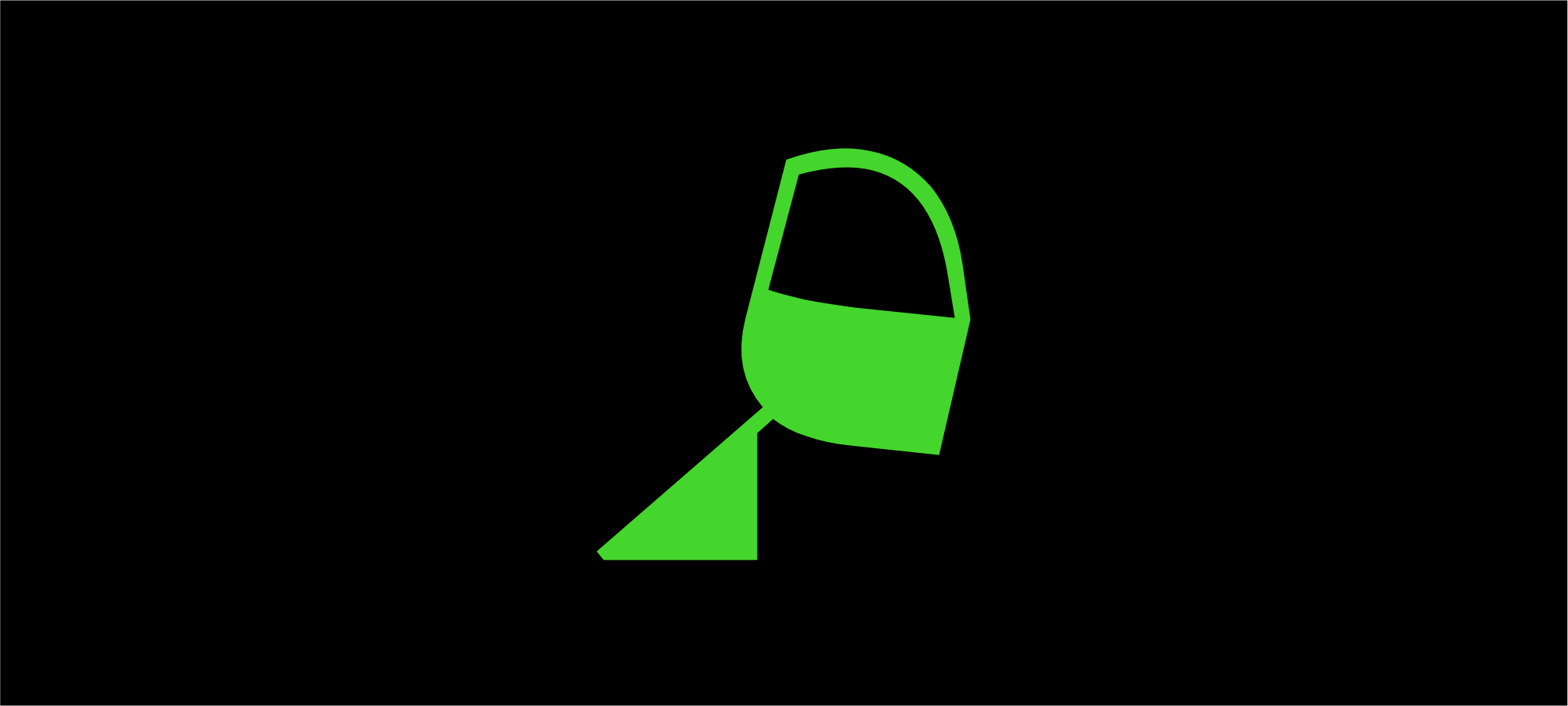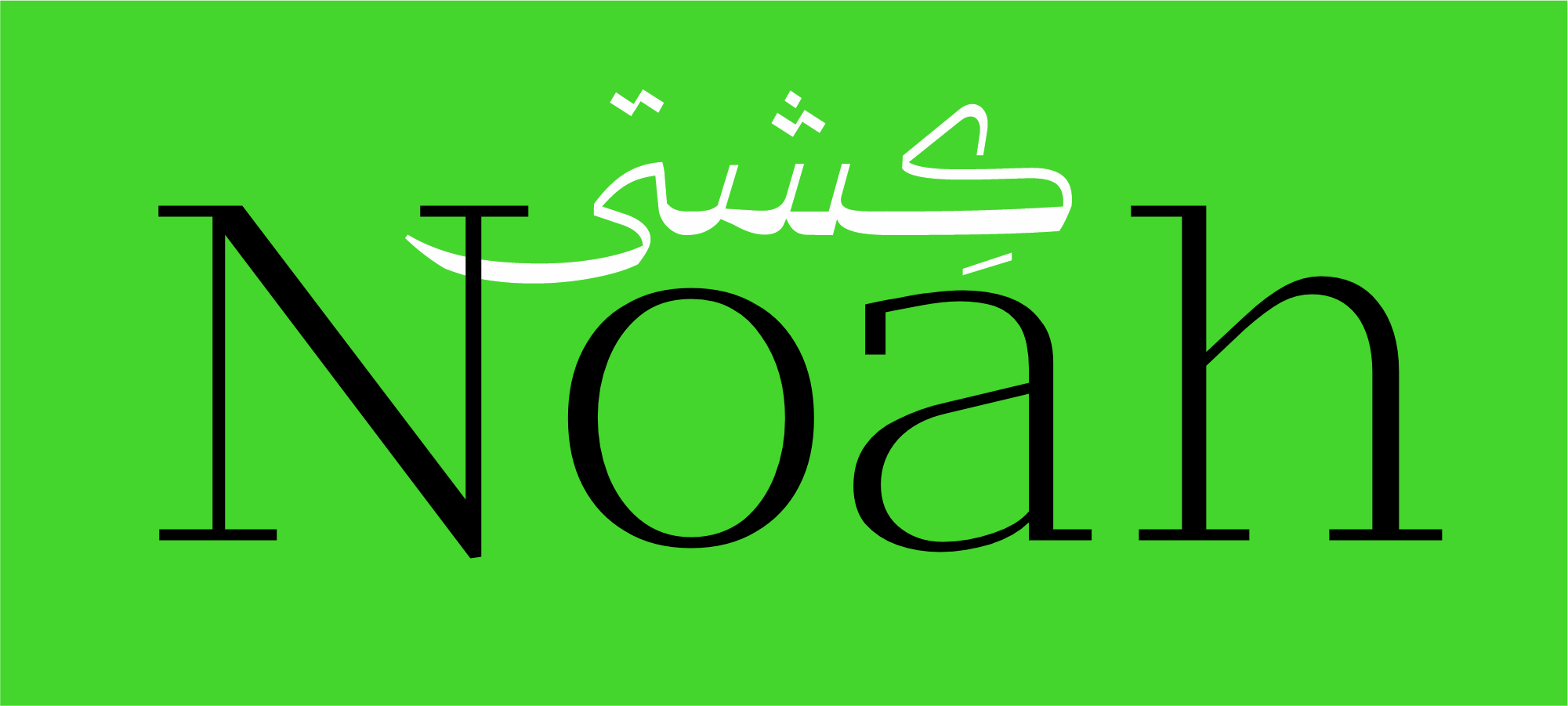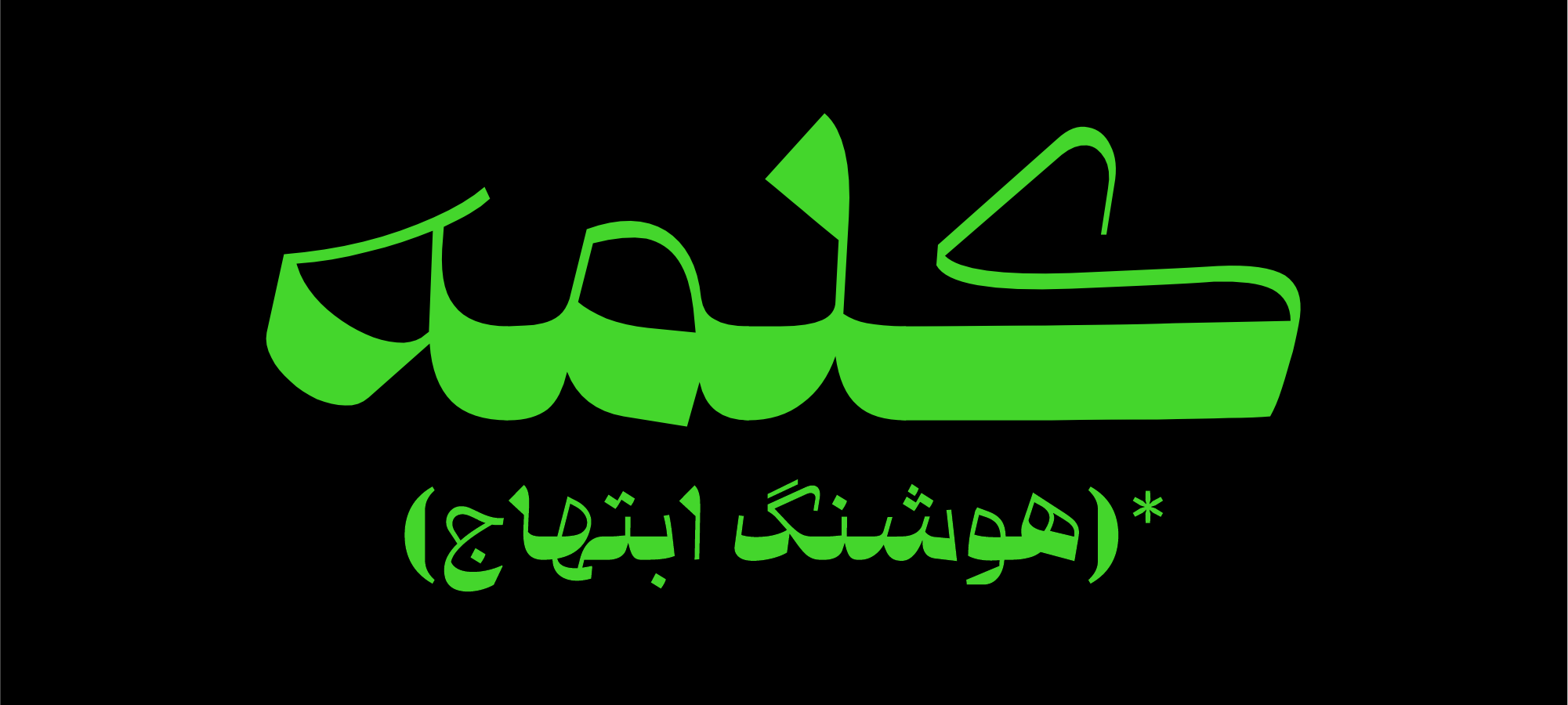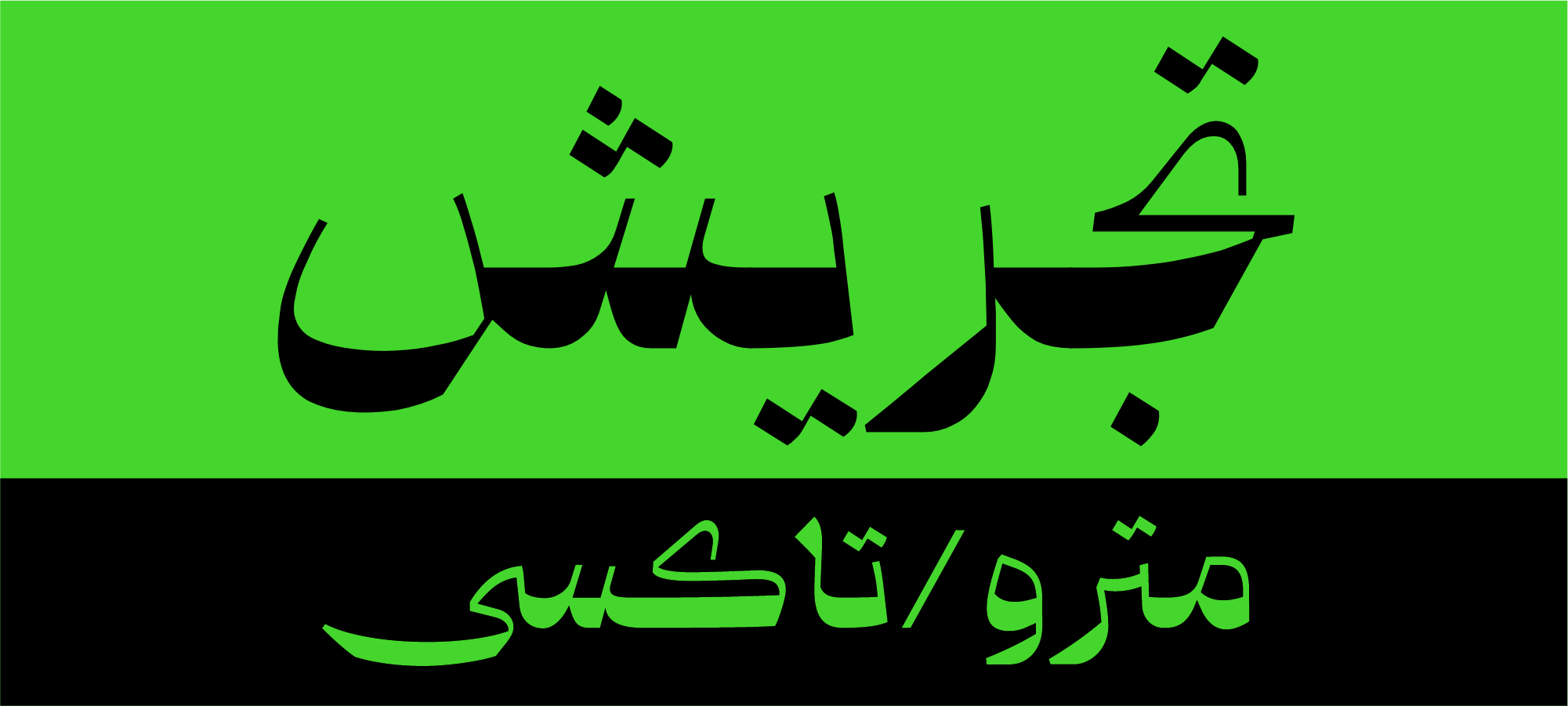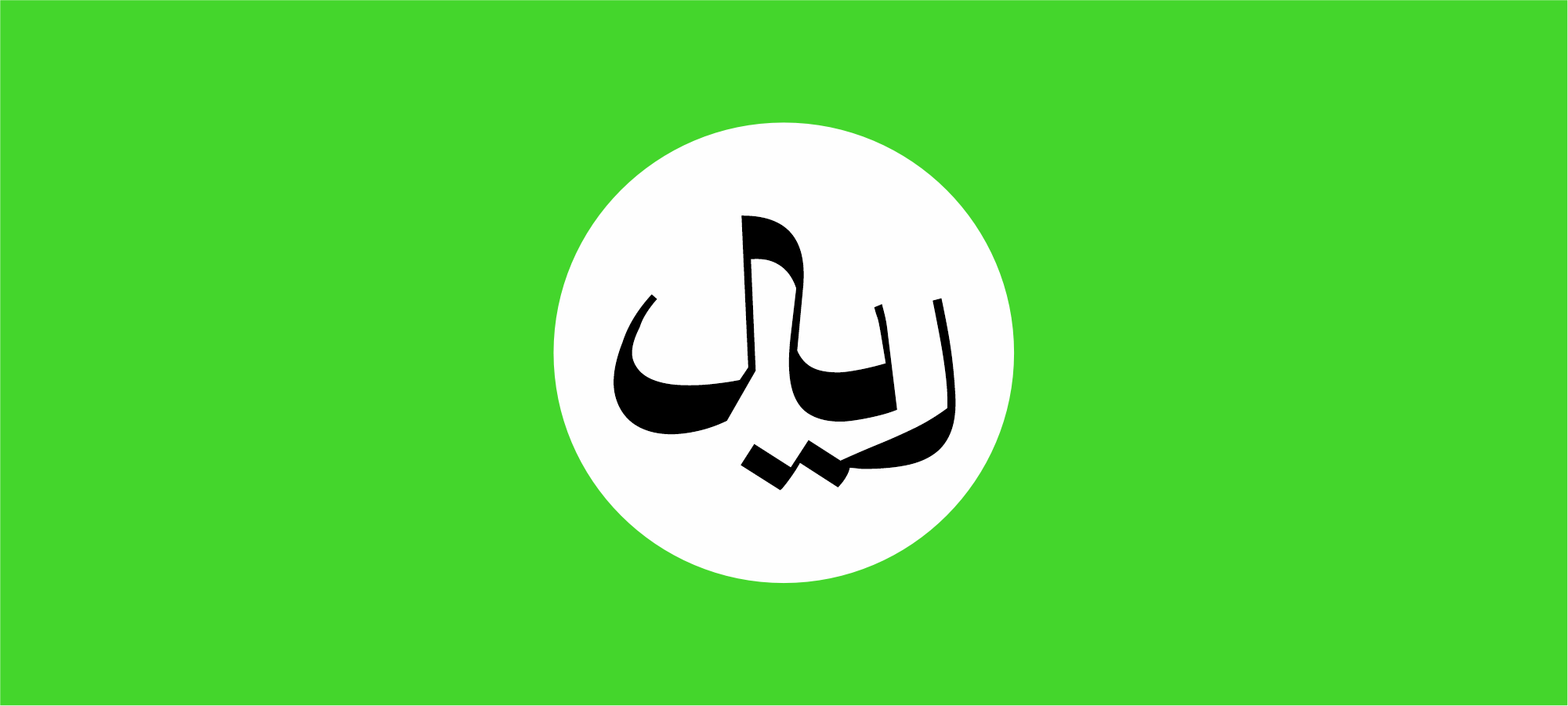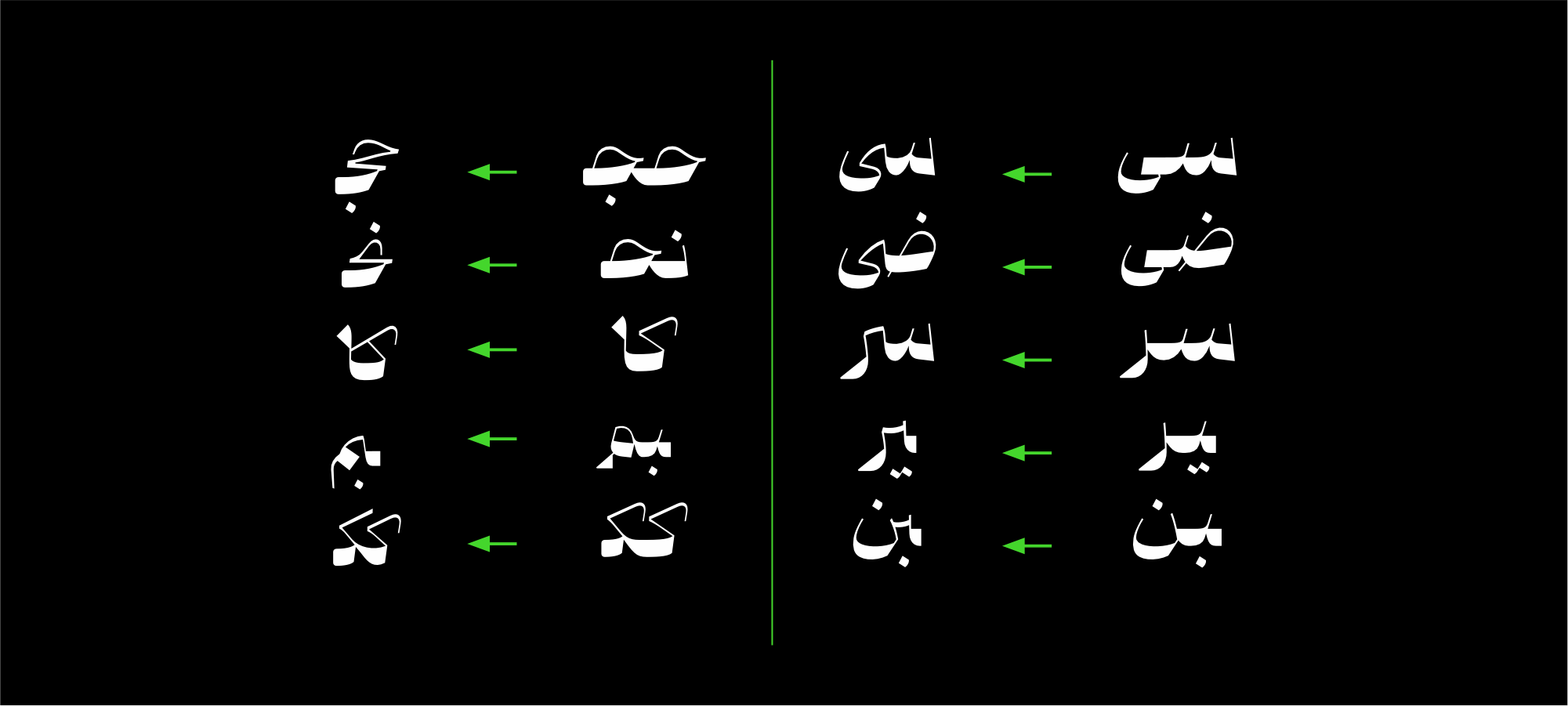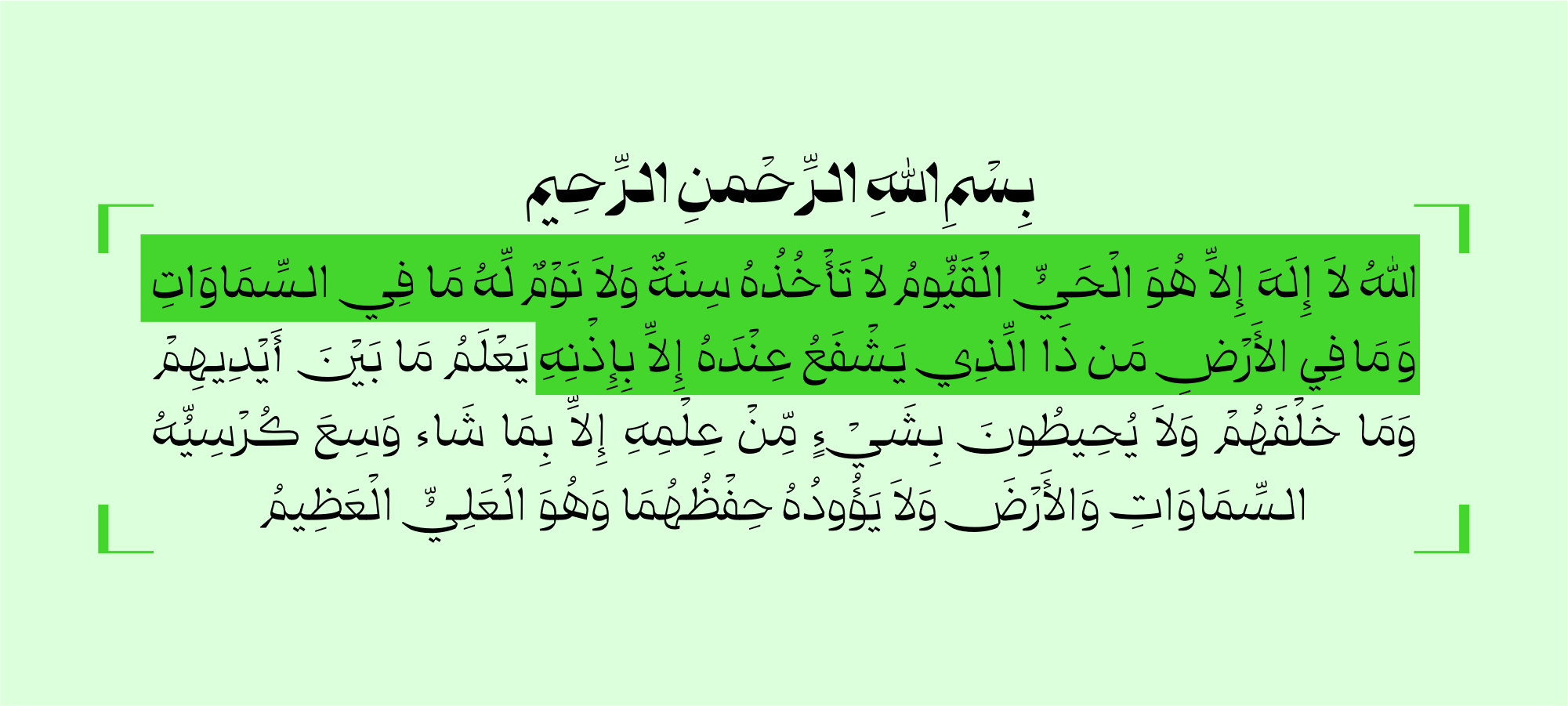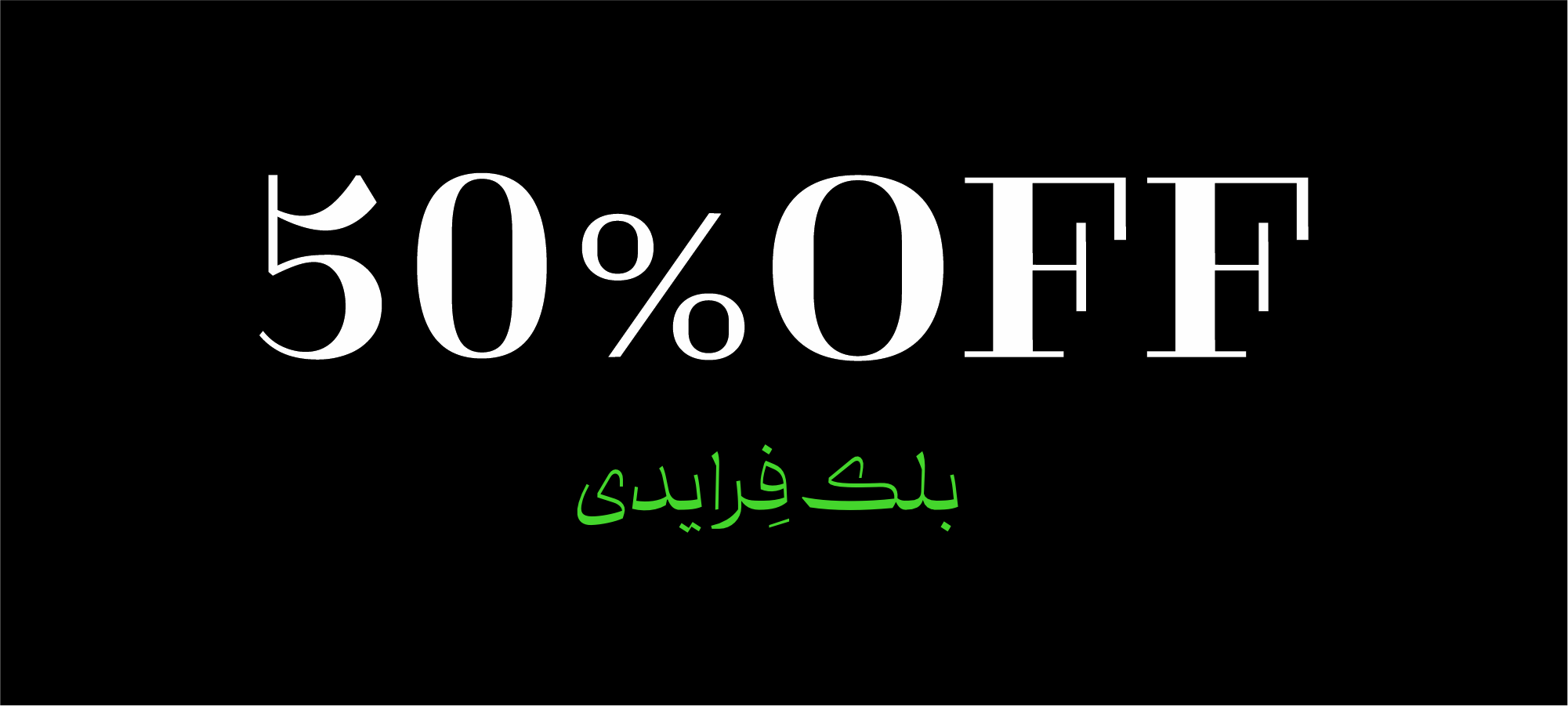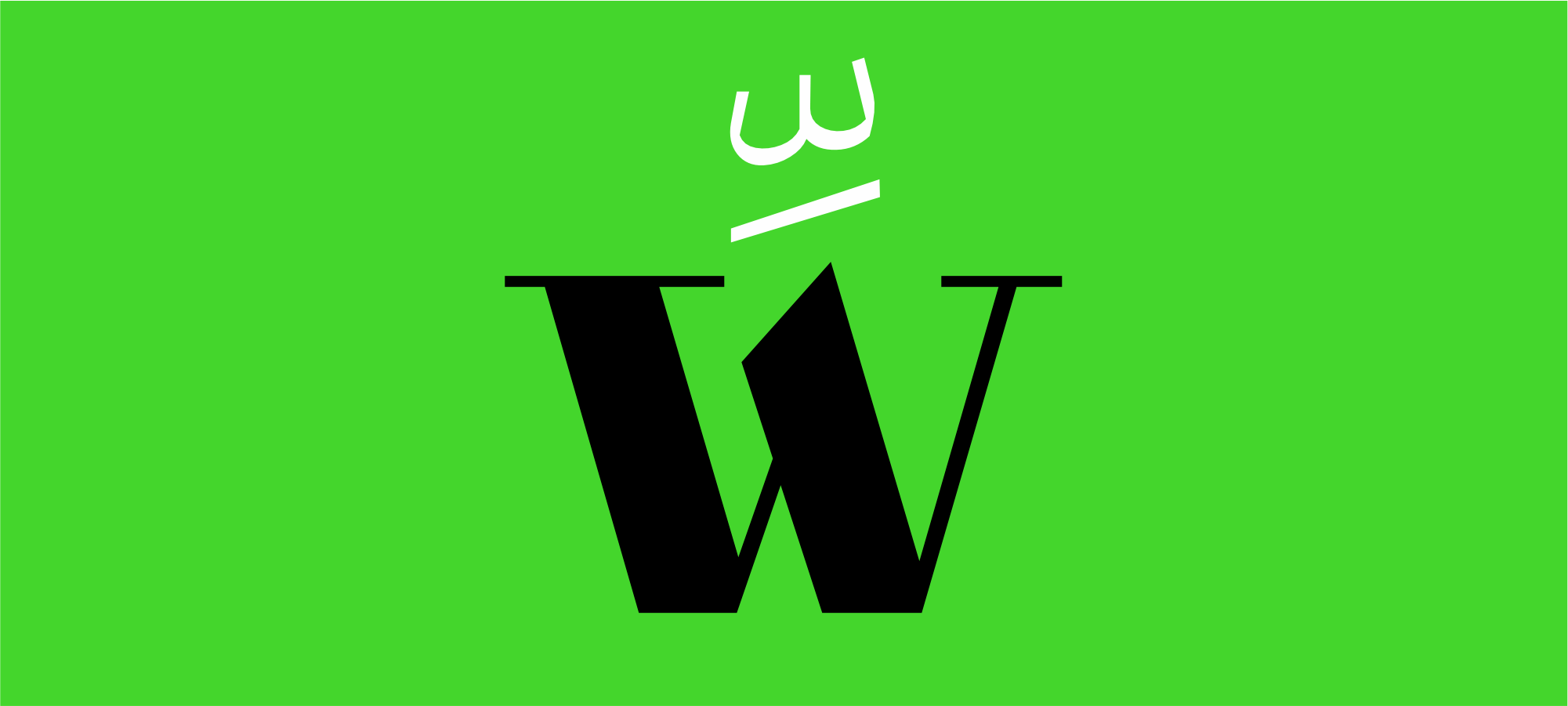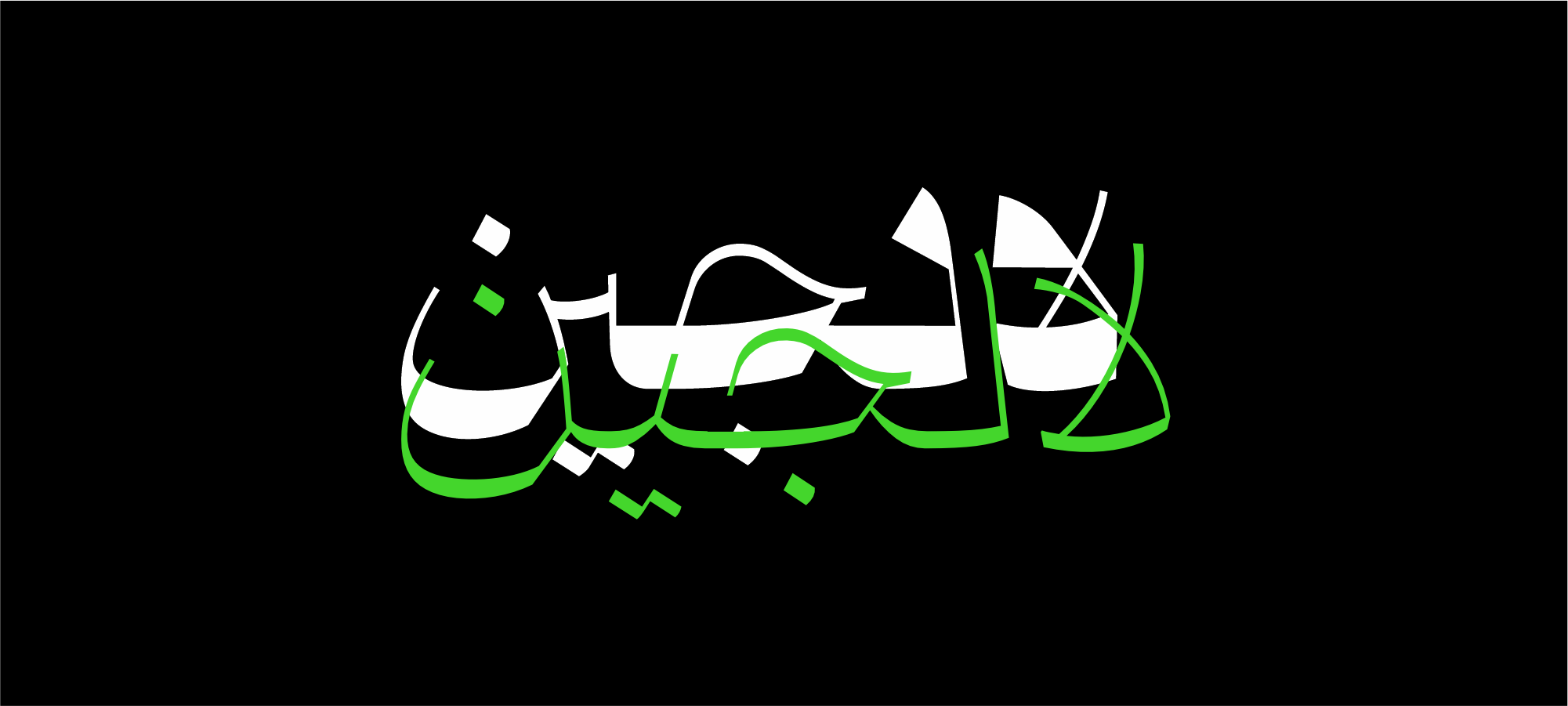
حروف کشیده / Swash letters
کشیدگیها با نگاهی به فرم های کشیده در خوشنویسی در فونت گنجانده شده و برای کنترل طول خطوط و زیبایی متون مورد استفاده قرار میگیرد. استفاده از کشیدگیها به تشخیص شما بستگی دارد.
برای استفاده از حروف کشیده در فونت قرنطینه (مانند: ـی،ـن، ـس، ـک، ـب) قابلیت swash را در نرم افزار فعال کنید. (راهنمای بسته فونت قرنطینه را مشاهده کنید.)
ترکیب های اختیاری/ Discretionary Ligatures
ترکیبهای اختیاری در تایپوگرافی مجموعهای از لیگچرهایی هستند که با الهام از ترکیبات خوشنویسی در فونتها تعبیه شدهاند و تزئینیتر از لیگچرهای استاندارد هستند. استفاده از اینترکیبها به تشخیص شما بستگی دارد.
برای استفاده از ترکیبی های اختیاری در فونت قرنطینه (مانند: ـین، ـسی، ـکک، ـیر، ـصی، نجـ، حجـ) قابلیت Discretionary Ligatures را در نرم افزار فعال کنید. (راهنمای بسته فونت قرنطینه را مشاهده کنید.)
ترکیب های الزامی / Required Ligatures
ترکیبهای الزامی مجموعهای از لیگچرهایی هستند که برای نمایش صحیح و روان خوانی الزامی میباشند. در فونت قرنطینه اتصالات "لا، ـلا " و عبارت مقدّس"الله" در نظر گرفته شده اند.
حروف لاتین / Latin Characters
در فونت قرنطینه، حروف لاتین به گونهای طراحی شدهاند تا با حروف فارسی همخوانی داشته باشند. اندازهها، تراکمها و ویژگیهای طراحی حروف لاتین با حروف فارسی هماهنگ هستند و همنشینی زیبایی را به وجود میآورند.
تنوع وزن
خانواده فونت قرنطینه دارای 9 وزن و 4 استایل Optical Size میباشد . این تنوع سایز و استایل ها امکان استفادهای گسترده ای را، از چاپ گرفته تا فضای مجازی پیش روی شما قرار میدهد.
طراحی / Design
طراحی خلاقانه و ابداع فرمهای نوین از ویژگیهای بارز فونت قرنطینه محسوب میشوند. تمرکز بر استفاده از سطح در مقایسه با دور و برجستهسازی شکستگیها در برابر منحنیها و همچنین رفتار پویا در تغییر ضخامت حروف، هیجان و جاذبهای خاص به این فونت بخشیده است.
اصلاح ضخامت های کم / Optical Size
در فونت قرنطینه چهار سبک در نظر گرفته شده است که ضخامت خطوط باریک را تعیین میکند. برای نمایش بهتر خطوط باریک در سایزهای کوچک، توصیه میشود که از مقدار کمتر برای optical size استفاده گردد.